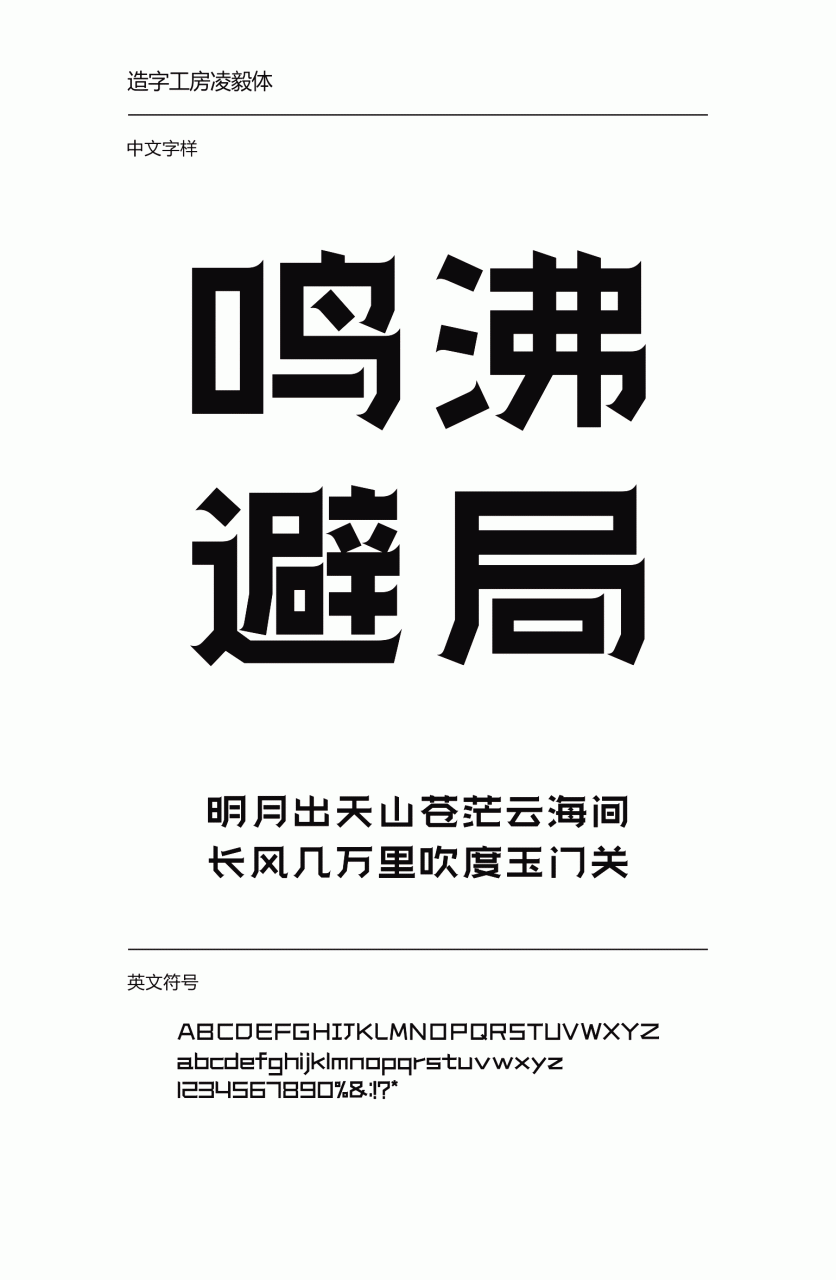
字体简介
造字工房凌毅体,字形扁方,整体风格庄重质朴,结构端正、严谨,笔画收笔以雁尾出锋,笔简意足,形意翩翩。此款字体适用于文字标题、广告设计、企业宣传等视觉环境,有着极强的应用空间。 本字体为简体字库,采用OpenType/CID格式,Adobe-GB1-5编码。基于中华人民共和国GB2312-80字符集标准,另按需添加101个汉字。共收容字数6864CJK汉字,ASCII常用字符100个。